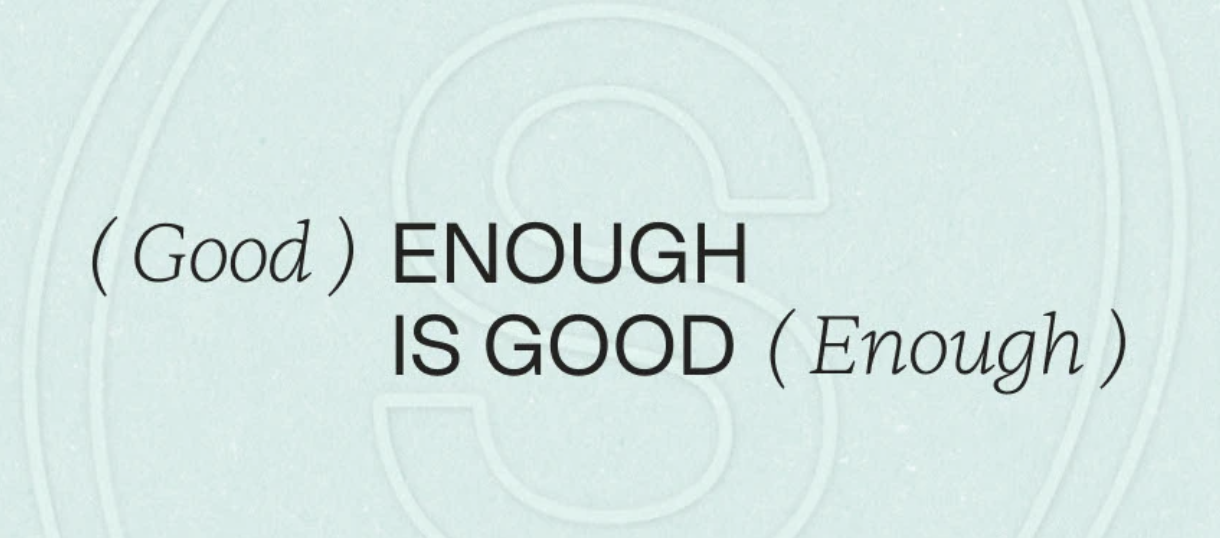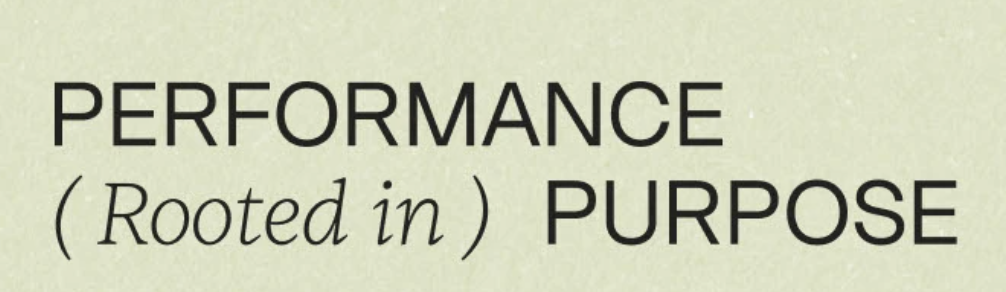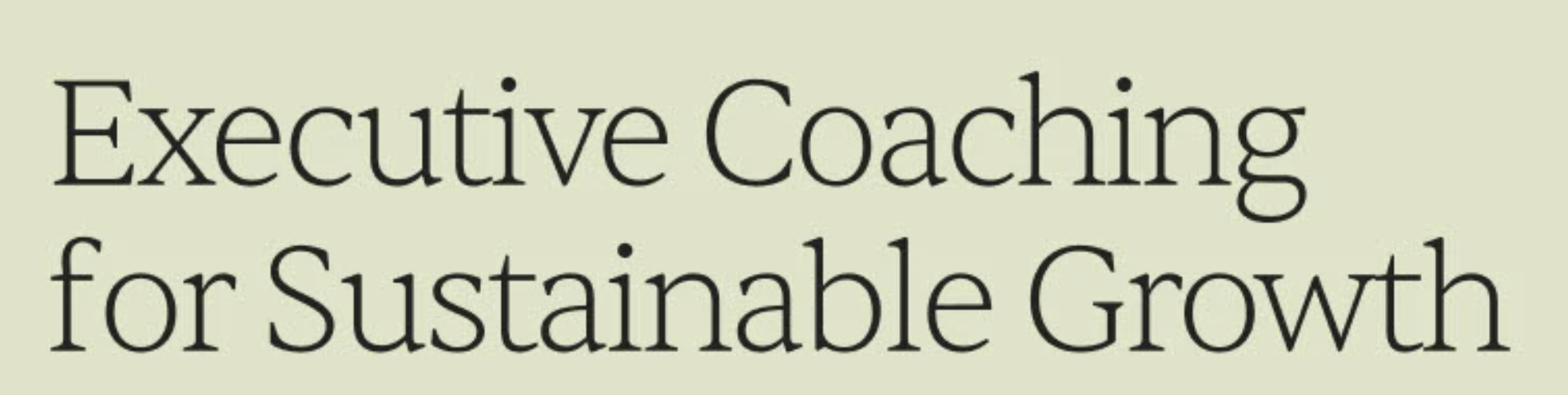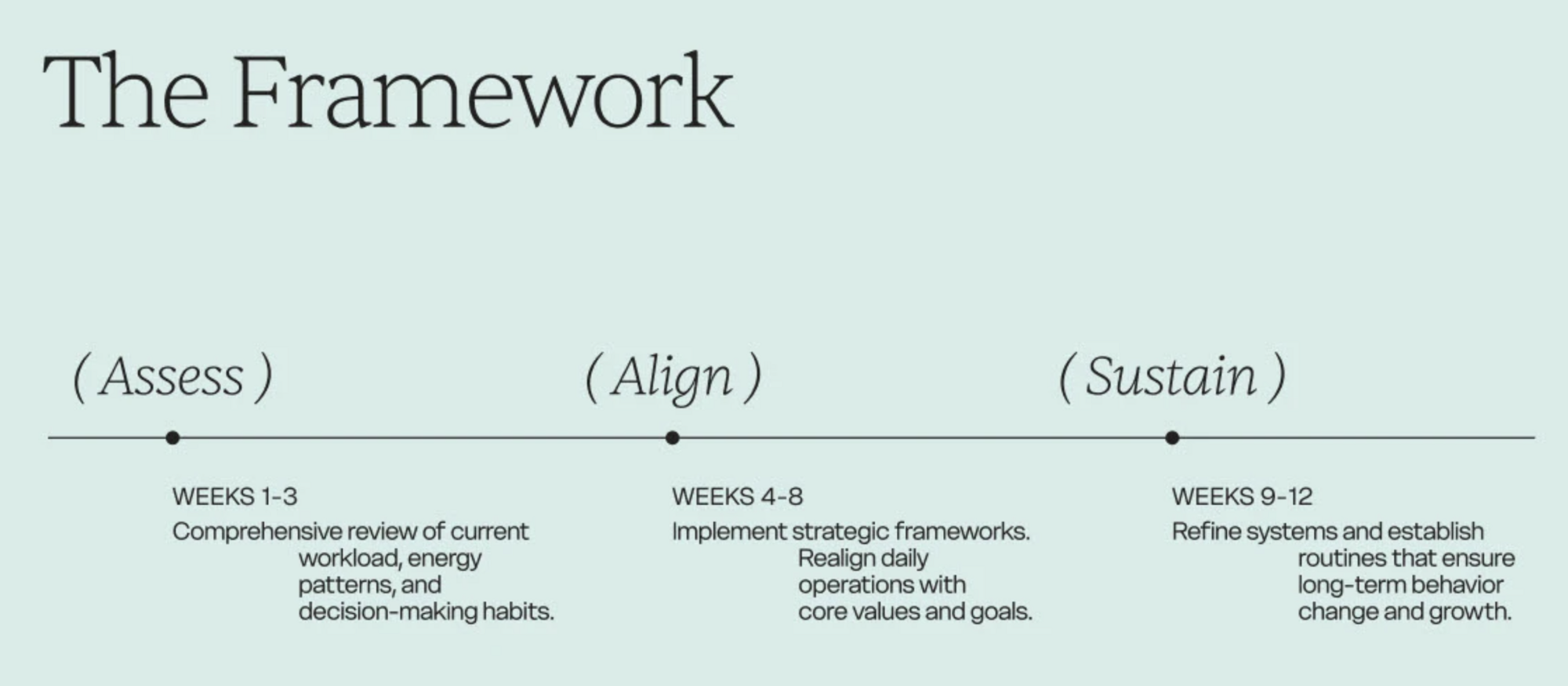
Ich bin auf der Suche nach den Namen (drei) Schriften die in diesem SAGERLY-Brandingbeispiel kombiniert wurden
Ich hoffe jemand kann mir behilflich sein und mir sagen welche drei Schriften (Serif italic, Serif und Grotesk) in diesem Branding kombiniert wurden:
Ich habe ein Projekt in dem ich eine sehr ähnliche Kombination verwende, jedoch ist meine Schrift sehr unschön geschnitten weswegen ich nach einer besseren Alternative suchte. Dabei bin ich über die Kombination (im Link) gestolpert und jetzt dringend auf der Suche nach den exakten Schriften.
Mal versucht direkt Kontakt mit Oleksandra aufzunehmen? Sie kann Dir sicher noch die Serifenlose verraten. 😉